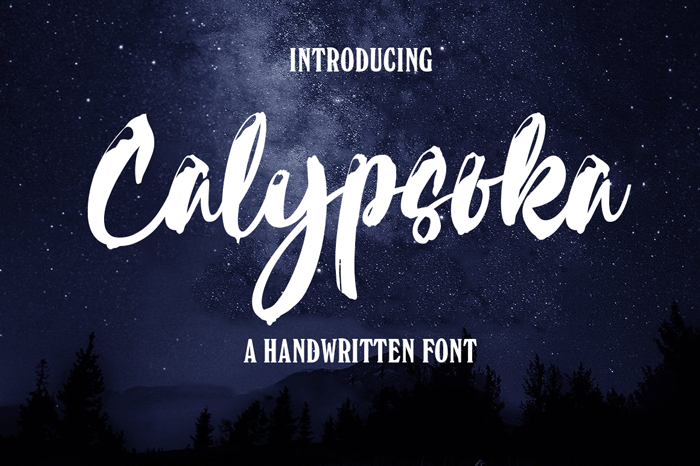
A Calypsoka Font é uma elegante e versátil escolha para designers buscando adicionar um toque autêntico a seus projetos digitais. Feita com a mão por Hamilton, esta fonte script se destaca graças à sua fluida escrita e detalhes cuidadosamente elaborados que refletem o espírito tropical do Brasil. Ideal tanto para trabalhos de texto quanto para logotipos e letras tipo, ela traz um toque nostálgico ao design moderno. Para usufruir dos benefícios completos desta fonte incluindo a possibilidade de uso comercial, os interessados podem contatar . Sua liberdade criativa é garantida com uma licença que permite explorar e experimentar as infinitas possibilidades que essa beleza única pode oferecer.